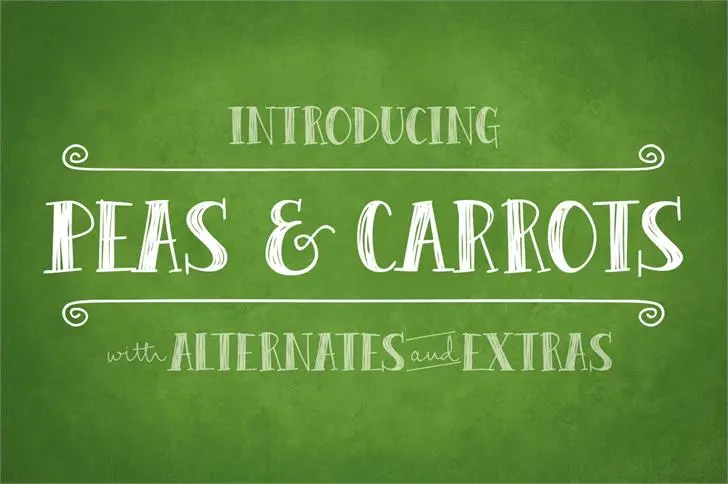
Peas & Carrots font
A fonte Peas & Carrots é uma atraente escolha para qualquer projeto visual, especialmente os design gráficos que valorizam um toque minimalista e criativo. Criada por Brittney Murphy Design em 2015, essa fonte de tipografia display destaca-se com sua aparência esbelta e em letras maiúsculas. O designer Hamilton incorporou elementos adicionais para a experiência do usuário, incluindo versões alternativas de letras minúsculas que permitem uma aparência ainda mais personalizada, como se fossem desenhadas à mão. Além disso, Peas & Carrots vem acompanhada de um “extras” font que contém palavras em destaque e banners, tornando-a uma opção versátil para criações digitais. Esta característica especial oferece a possibilidade de personalizar seus projetos ainda mais, permitindo uma variedade incrível de combinações e usos criativos. Esta font é ideal tanto para designers profissionais quanto para amantes do design que desejam dar um toque único em seus trabalhos. Suas linhas clean e a capa esbelta proporcionam uma visão atraente e envolvente, tornando-a uma opção primordial na gama de fontes disponíveis no mercado.